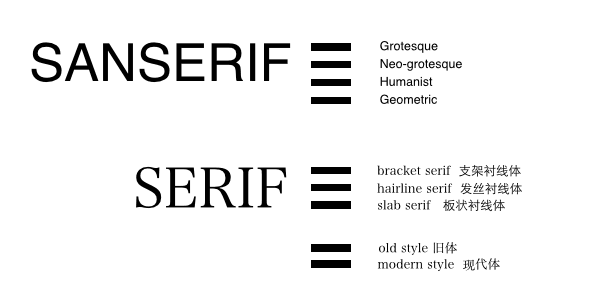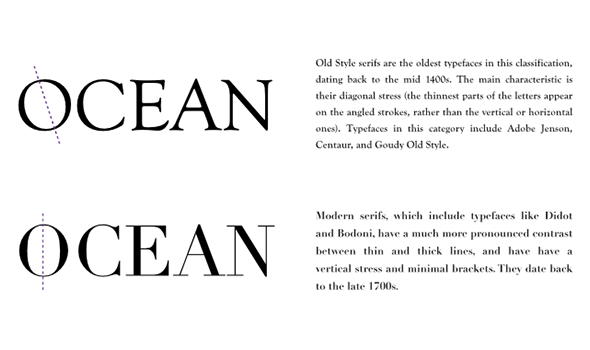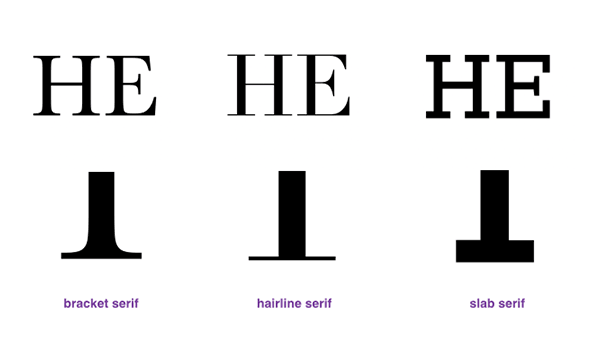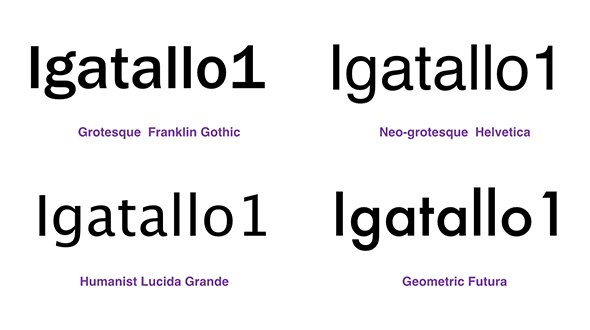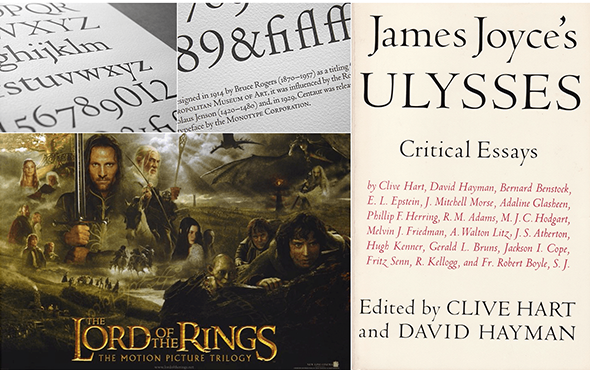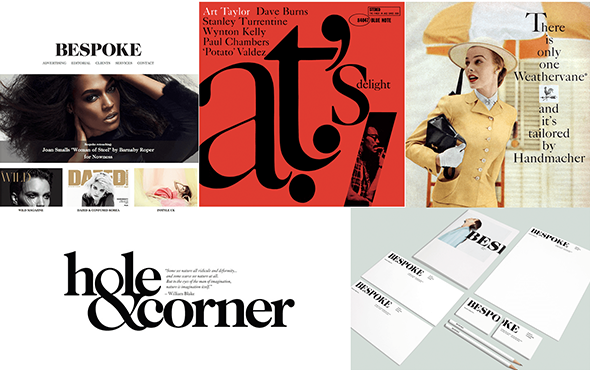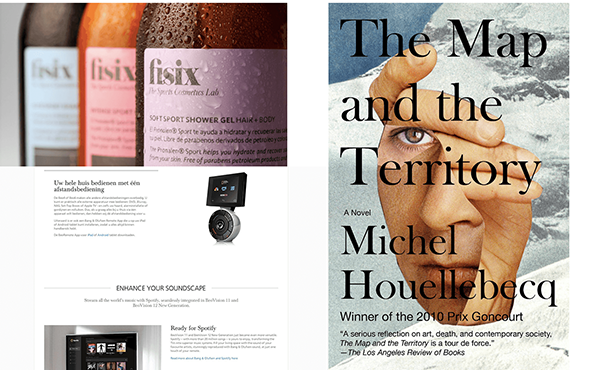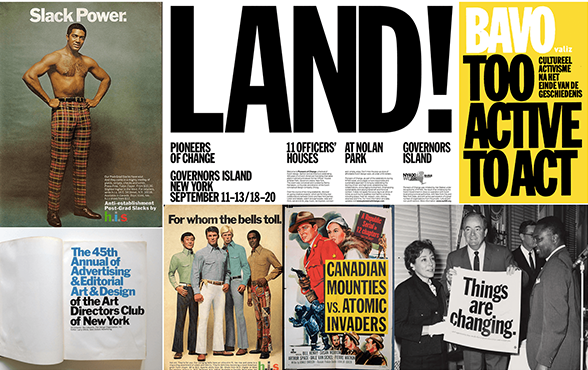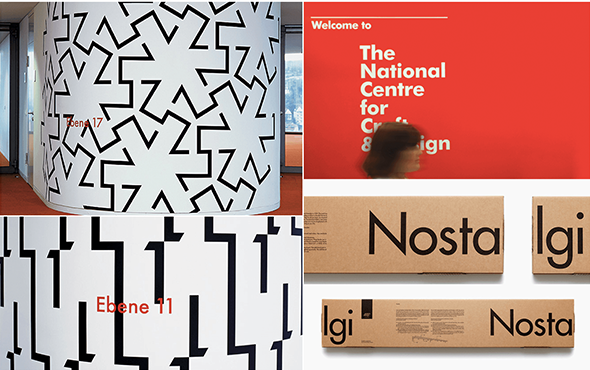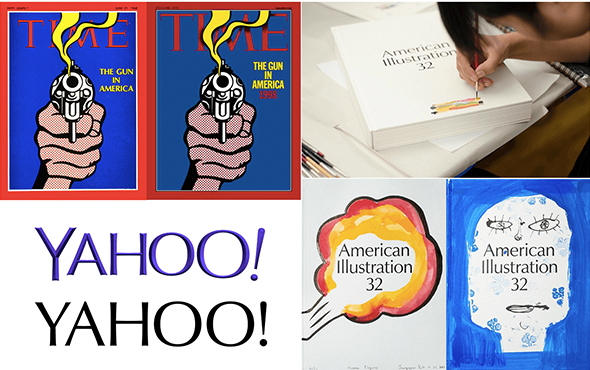
字體是視覺設計中最重要的傳達元素之一,字體本身的視覺特性和品質影響著訊息傳遞的質量,英文字體有自己非常完善的系统,如果要精通則需要從字體的歷史與形成,文化屬性細細研究,限於文章篇幅,這裡只從個人的感受出發寫一些更偏向於應用的内容。
英文字體的分類
英文文字大致分成三類「襯線體」、「無襯線體」和「其他字體」。其他字體包括哥特體,手寫體和裝飾體,这些字體在我們工作中使用相對較少,所以重點介紹襯線體和無襯線體兩大類。
襯線體的歷史比較悠久,是古羅馬時期的碑刻用字,適合用於表達傳統,典雅,高貴,距離感。
襯線體可以分成兩類:類似手寫的襯線體叫“舊體”,筆尖會留下固定傾斜角度的書寫痕跡,O字母較細的部分連線是斜線。舊體並不意味過時,傳統書籍正文通常用舊體排版,適合長文閱讀。
比例工整,沒有手寫痕蹟的襯線體叫“現代體”。 O字母較細部分連線是垂直的。體現了明快的現代感,給人冷峻、嚴格的印象,這種襯線體縮小後文字易讀性比較差,一般在標題上使用。
襯線體還有另外一種分類方式,根據襯線變化可以分成三類:具有特定曲線的襯線為“支架襯線體”,連接處為細直線的是“髮絲襯線體”,厚粗四角形的“板狀襯線體”。
支架襯線體是舊體中最常見的字型,在襯線體中相對親切、傳統。比較常見的字體有Times New Roman,Baskerville,Caslon,Georgia。
髮絲襯線體是現代體中常見的字型,具有明顯現代感,不適合磅值小的字體。比較常見字體有Didot,Bodoni。
板狀襯線體比較有力,是19世紀到20世紀初用在廣告牌上的文字,多用於標題,具有懷舊氣氛。
無襯線體相對襯線體更加親和,現代。從類別上大致可以分成四類:Grotesque, Neo-grotesque,Humanist和Geometric。
Grotesque是最早出現的無襯線體,所以保留了一些襯線體的特徵,比如小寫字母g的寫法不一樣,數字1下方有粗襯線。
Neo-grotesque包括很多常用字體,Helvetica,Arial,Univers,不帶情緒,冷靜簡潔。
Humanist有一點書法感,給人溫暖的典雅氣氛,有一點女性氣質,識別度非常好,網站正文字體常用。
Geometric字體趨近幾何形狀,例如字母O非常像正圓,字母a是半圓加一個尾巴,易讀性不好所以不適合用在正文,但是這類字體有非常強的設計感。在某些需要突出設計感的場合用磅值大的字體效果很好。
個人感覺從趨勢上而言humanist和Geometric使用率越來越高,尤其是web端Humanist慢慢在侵蝕Neo-grotesque的領地。
經典字體推薦
當我們不確定用什麼字體的時候不妨先確定什麼類別的字體最合適,襯線還是非襯線,人文體還是幾何體,確定好了之後再多考慮看看一些經典字體是否可以使用,下面推荐一些經典字體。
具有史詩般正統風格,特別適合用於表現年代悠久。具體排版時注意合字和老式數字的使用。
復古傳統,沒有強烈個性,十分易於閱讀,因為太流行所以很多大的公司都做過Garamond復刻,蘋果電腦裡有系統字Garamond以及Adobe所製作的Adobe Garamond Pro。如果是希望web上使用,可以考慮EB Garamond。
美國獨立宣言用字,是活字時代的大熱字體。很多公司也做過Caslon復刻,現在的使用也非常廣泛。
過渡期羅馬體(舊體到現代體)的代表性字體,非常經典,給人古典、高貴的感覺。
現代襯線體,髮絲襯線。特點是強烈的筆劃粗細對比和水平襯線,時尚,現代,優美。
與Didot類似,適合大字體表現,相對Didot來說硬朗一點。
這款字體是很早出現的無襯線體,所以帶有古風,筆劃粗狂有力,具有男性化感覺,適合表現強有力。 Web字體可以考慮Oswald。
Futura是拉丁語未來的意思,現代且具有幾何特徵,感覺是現在的主流大熱字體,尤其是要突出時尚,設計感的時候可以使用。製作過程中受到包豪斯運動的影響。是LV的商標用字,也是現在很多雜誌的首選字體。
英國風格的代表字體,具有古典風格的骨架,但是又有很強的科技感和未來感,字體外形偏幾何,但是是humanist字體,相對futura會柔和一些。
有古典氣息,筆劃兩端比較粗中間比較細,氣質優雅。時代周刊的字體更換,雅虎2013年使用Optima作為全新標識的設計基準都證明了這款字體的熱度。
Grotesque字體,比Helvetica更加簡練。字體家族非常全面,所以搭配使用很方便。
Humanist字體,很早就已經流行,隨著蘋果的廣泛使用更加引人注目,筆劃柔和簡潔。
字形簡潔,現代,雖然也有幾何特徵,但是不失人情味。 Avenir是法語未來的意思,對同樣未來含義的Futura是一種挑戰,放大x-height,降部拉長,使得文字的易讀性明顯提高。字體家族也很完整。
最後提兩句Helvetica,內部分享的時候很多設計師問到為什麼沒有作為一個推薦字體在這裡列出,一方面是因為Helvetica已經作為現代字體中的經典字體被應用得非常廣泛了,並不缺乏關注。另一方面Helvetica是Neo-grotesque字體,結構嚴謹,沒有情緒導向,提供著強烈的安全感,好像怎麼用都不會錯,這是個優勢也是個劣勢,當我們的設計有比較明確的受眾群體或者設計對像有比較明確的氣質的時候能夠尋找到有同樣氣質的字體會是更優的選擇。
適合長文閱讀的文字
無襯線體中適合長文閱讀的文字一般是Humanist,襯線體中適合長文閱讀的文字一般是支架襯線體。下面列幾個個人覺得比較適合排長文的字體。
無襯線體:Lucida Grande, Roboto, Open Sans
襯線體:Georgia, Droid Serif, Cambria
適合長文排版的字體還有很多,比如無襯線體中的Lucida Sans,Geneva,襯線體中的freight text,看一些比較好的設計的時候不妨多留心一下字體用的是什麼。
字體應該怎麼搭配
字體搭配總體的原則是一致性加對比性。一致性指的是選擇調性和情緒一致的字體。比如現代羅馬體搭配幾何無襯線體,古典羅馬體搭配年代比較久遠的無襯線體。字體的情緒表達需要統一,嚴肅的字體並不適合搭配隨意的字體。
對比性是指字體之間要有較明顯的差異,不能感覺很像,分不開差異。
對比性也可以用很多種方式達成,上面列出的不同字體搭配是一種,不同的字重和不同樣式都可以,用字重來強調對比的話最好不要選擇相鄰等級,用隔一個等級的字款搭配。
最簡單的搭配方式就是用同款字體創造對比,另外一個很保險的方法是選擇包含有對比性字體的字體家族,比如ITC Stone Sans Std和ITC Stone Serif Medium以及Freight Sans Pro和Freight Display Pro。很多字體家族是同時包含稱襯線體和無襯線體的,它們在設計初始的時候就有相同的骨架,所以排版起來非常協調。